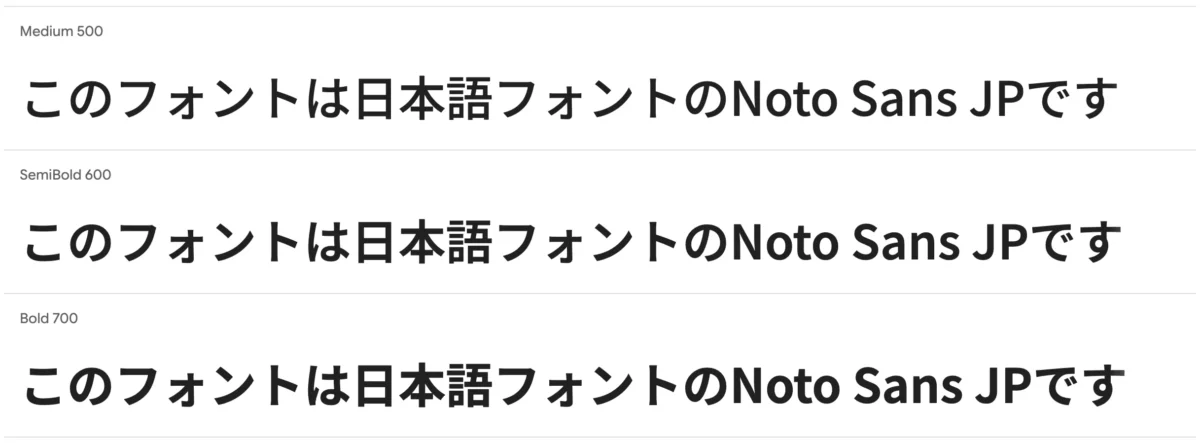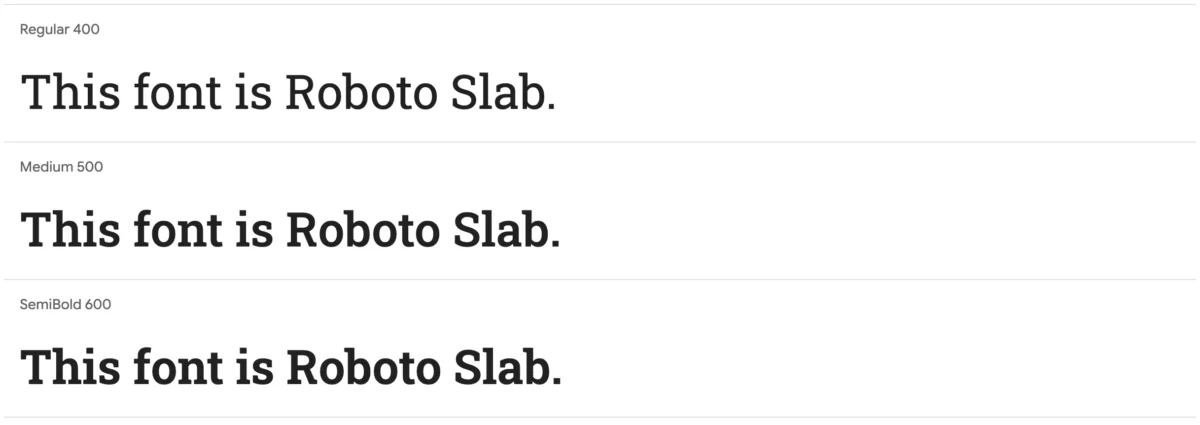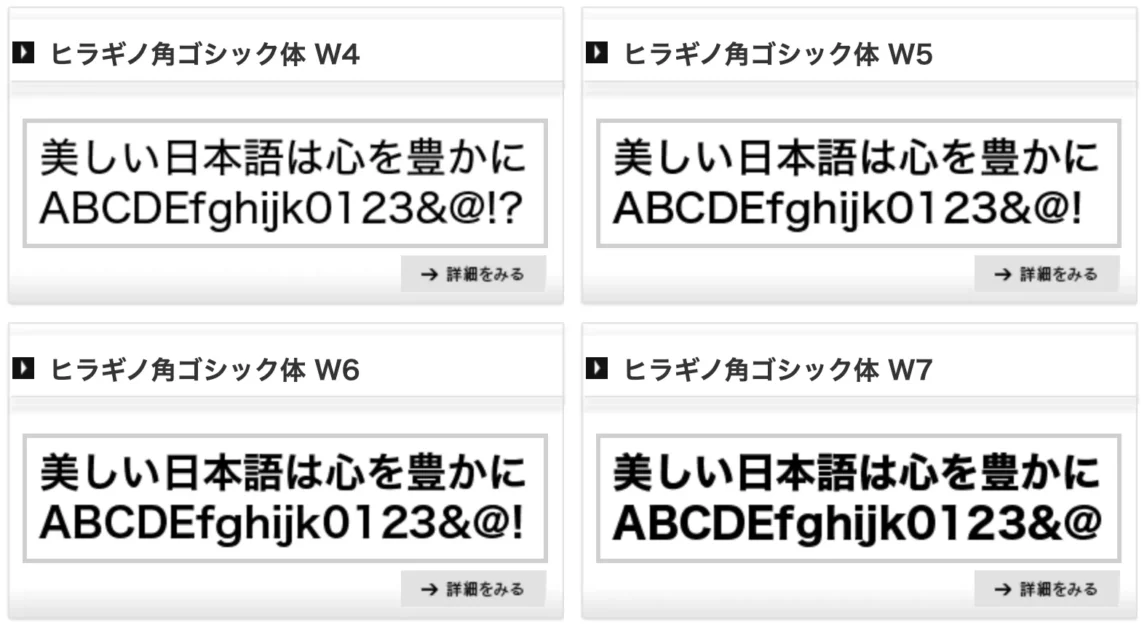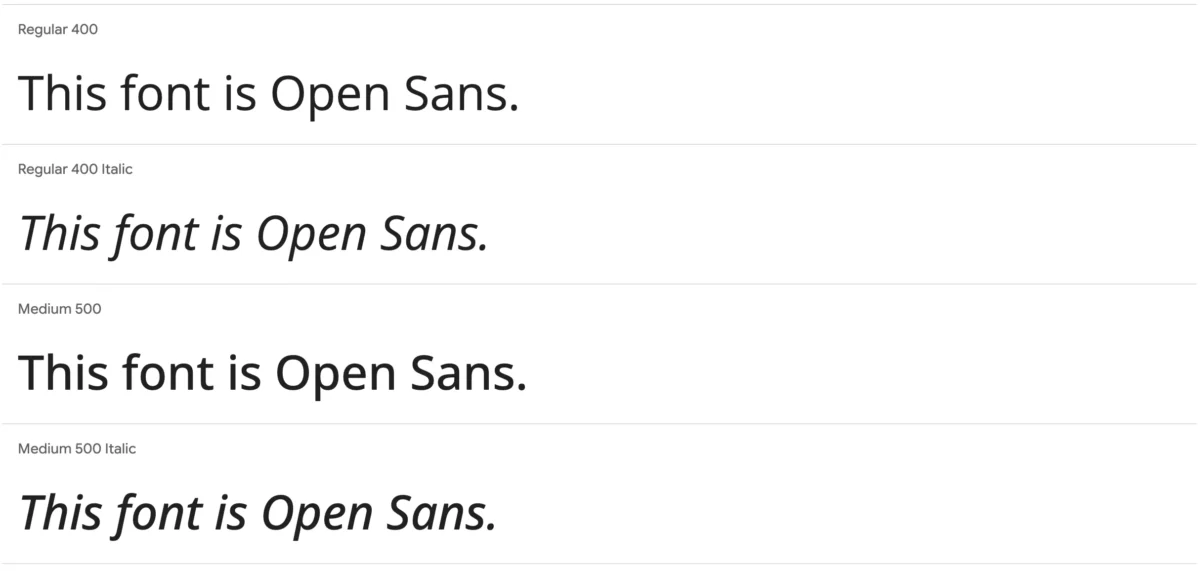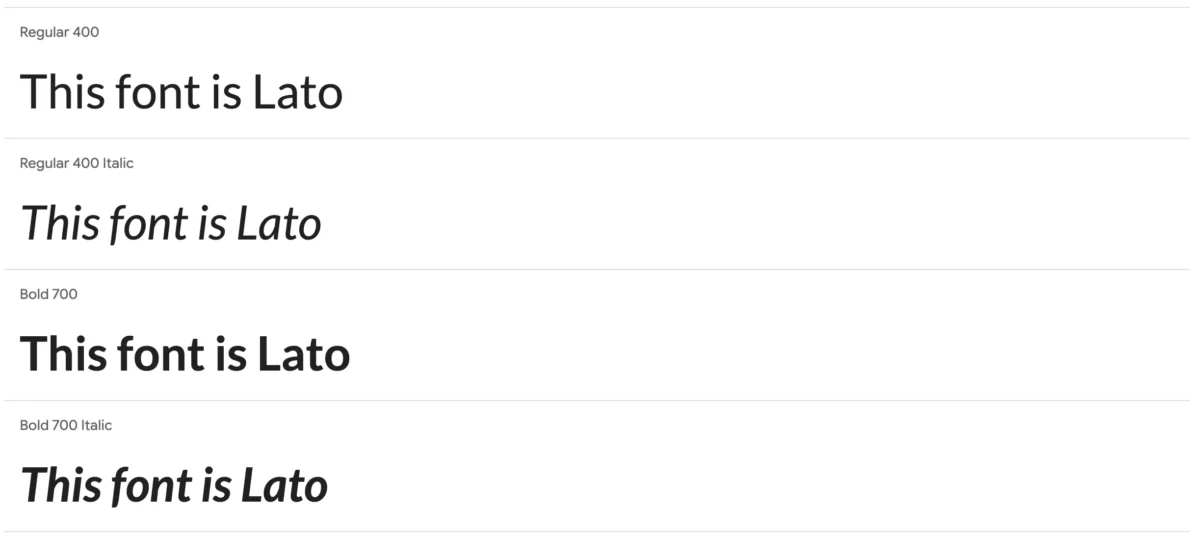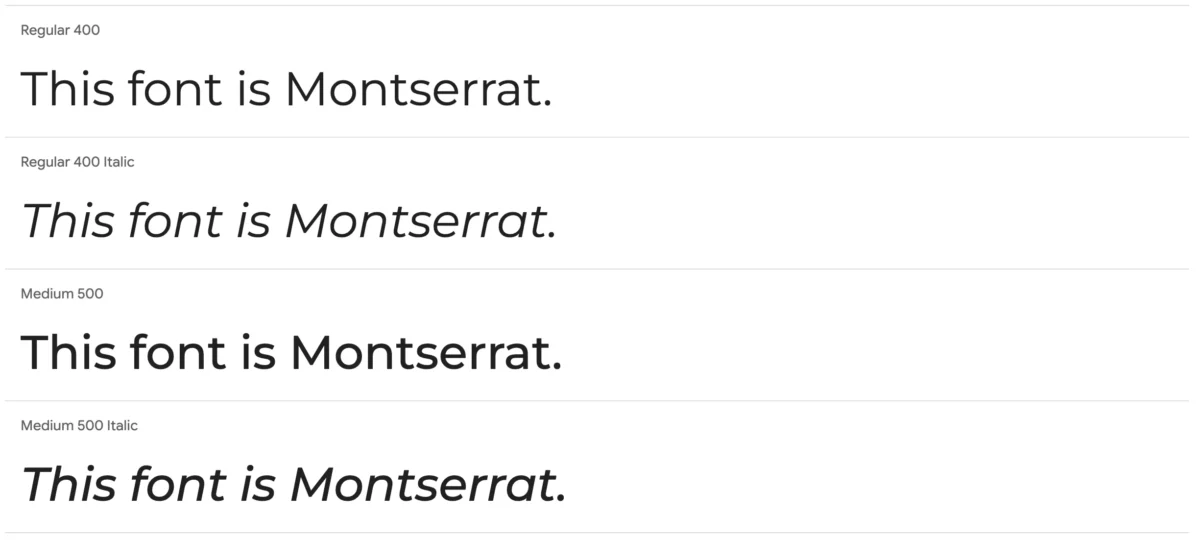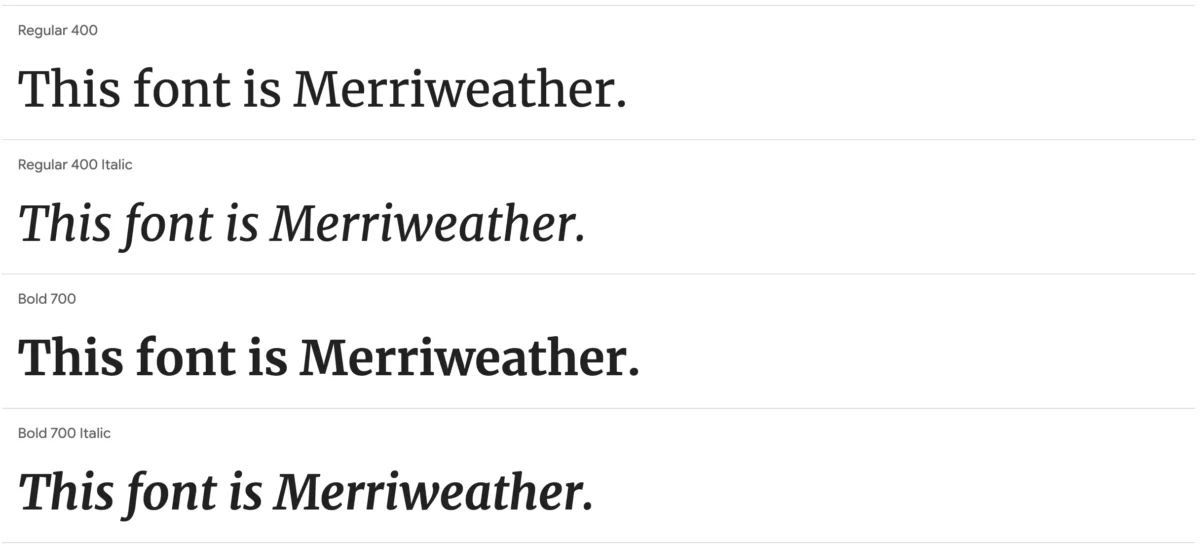
【2024年版】Webデザイナー必見!人気のWebフォント10選(日本語&英数字)とダウンロード
Webデザインにおいて、フォント選びはユーザー体験やサイトの印象を大きく左右します。
この記事では、Webデザイナーがよく使う日本語フォントと英数字フォントをそれぞれ5つずつ厳選して紹介します。
日本語フォント(おすすめ5選)
1. Noto Sans JP
Googleが提供する無料の日本語ゴシックフォントで、視認性とシンプルさが特徴。モダンなデザインやUI、Webサイトに幅広く使えます。
2. Noto Serif JP
Noto Sansのセリフ版で、明朝体風のエレガントなフォント。フォーマルなデザインや雑誌風レイアウトに最適です。
3. Roboto Slab
Google Fontsで提供される、洗練されたセリフフォント。日本語版もあり、可読性が高く、長文のWebコンテンツやブログに最適です。
4. ヒラギノ角ゴシック
macOSにプリインストールされている高品質フォントで、清潔感のあるモダンなデザインが特徴。商用ライセンスは有料です。
5. 游ゴシック体
Windows 10とmacOSの両方でプリインストールされており、モダンなデザインやUIに多用される日本語フォントです。
英数字フォント(おすすめ5選)
1. Roboto
Googleが開発したサンセリフフォントで、非常に多くのWebサイトやアプリケーションで採用されています。モダンかつシンプルで、UIデザインにも最適。
2. Open Sans
Google Fontsで提供されている人気のサンセリフフォント。可読性が高く、ブログやコーポレートサイトに多用されています。
3. Lato
柔らかなカーブが特徴で、フレンドリーでありながら洗練された印象を与えるフォント。Webデザイン全般で多用されます。
4. Montserrat
太めのサンセリフフォントで、タイトルや見出しに最適。モダンでスタイリッシュなデザインを強調したい場合におすすめ。
5. Merriweather
セリフ体でありながら、可読性を重視したフォント。特に長文コンテンツやブログ、ニュースサイトなどで人気があります。
まとめ
フォント選びはWebデザインの重要な要素であり、適切なフォントを選ぶことでサイトの印象や可読性が大きく変わります。上記で紹介したフォントは、どれも無料でダウンロード可能で、すぐにプロジェクトに組み込むことができます。
Webデザインにおけるフォント選びのポイント:
• 視認性を重視したフォントを選ぶ
• デザインのトーンやメッセージに合ったフォントを使う
• 日本語と英数字のフォントの相性にも注意する
あなたのプロジェクトに最適なフォントを見つけ、より魅力的なWebサイトをデザインしましょう!